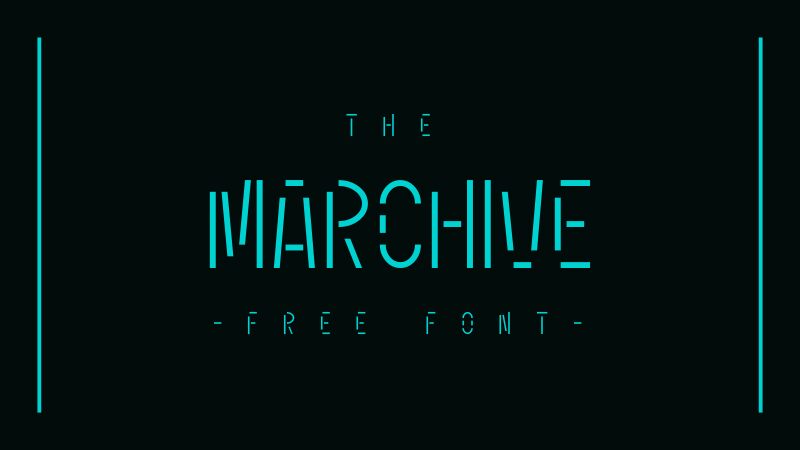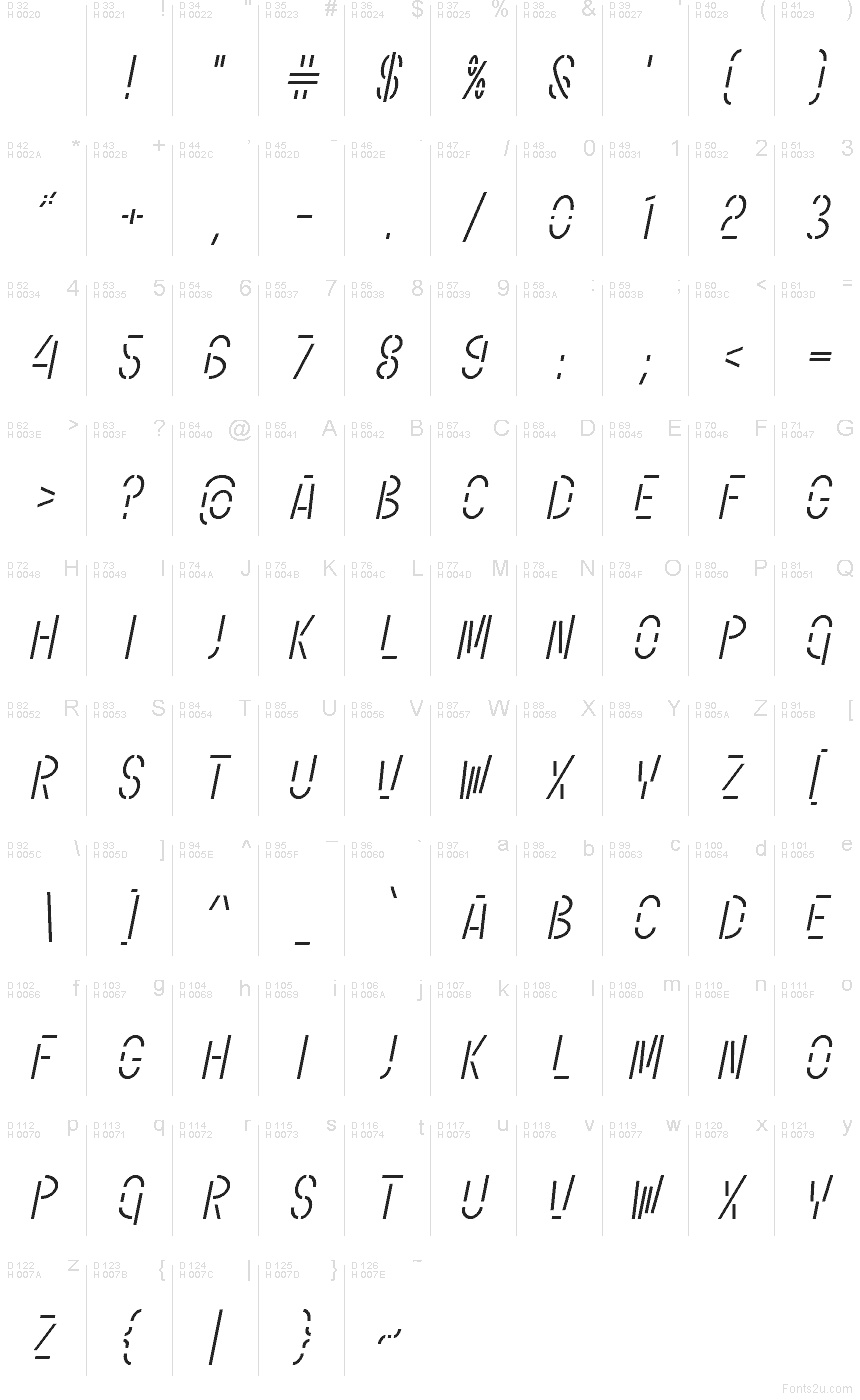
Marchive Italic
Marchive Italic, conçue par GGBotNet, est une police d'affichage techno gratuite. Avec ses formes inclinées et découpées ainsi que ses traits étroits, chaque caractère semble rythmé par un design mécanique et segmenté. Les courbes arrondies sont interrompues par des cassures nettes, tandis que les lignes droites conservent une simplicité angulaire, offrant un style futuriste et codé sans fioritures inutiles.
Marchive Italic est idéale pour les logos de jeux vidéo, les affiches d'événements technologiques, les titres de science-fiction, les bannières d'applications et les signatures de marque où la structure oblique affirme le design. Cette police gratuite est également parfaite pour les titres d'affiches, le packaging et les créations numériques, car ses formes fracturées apportent une esthétique mécanique affirmée aux textes courts.